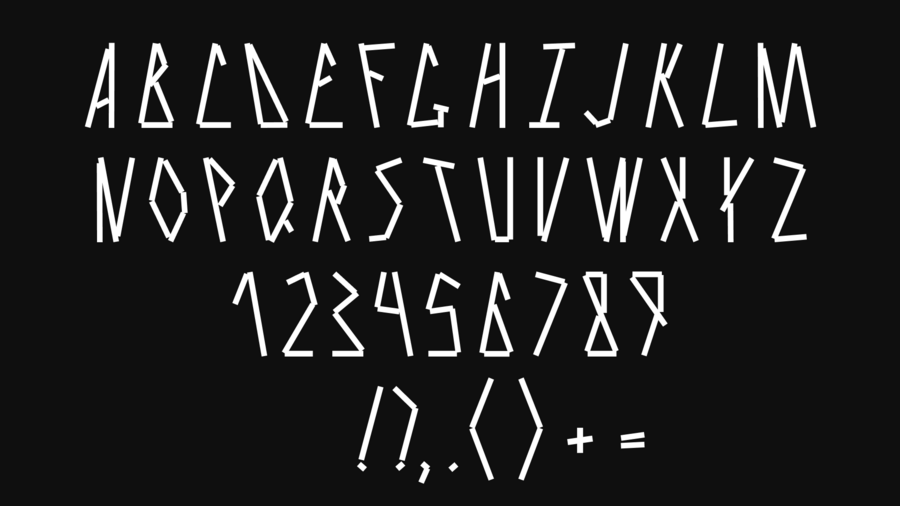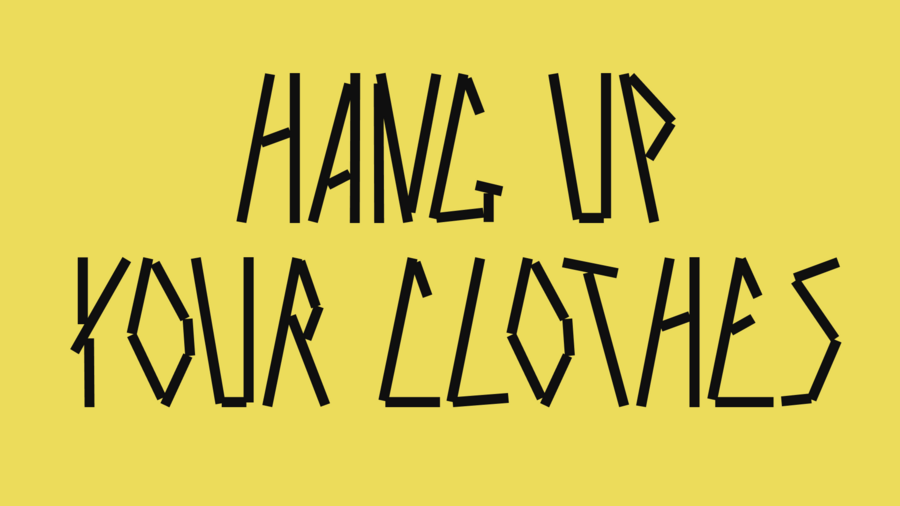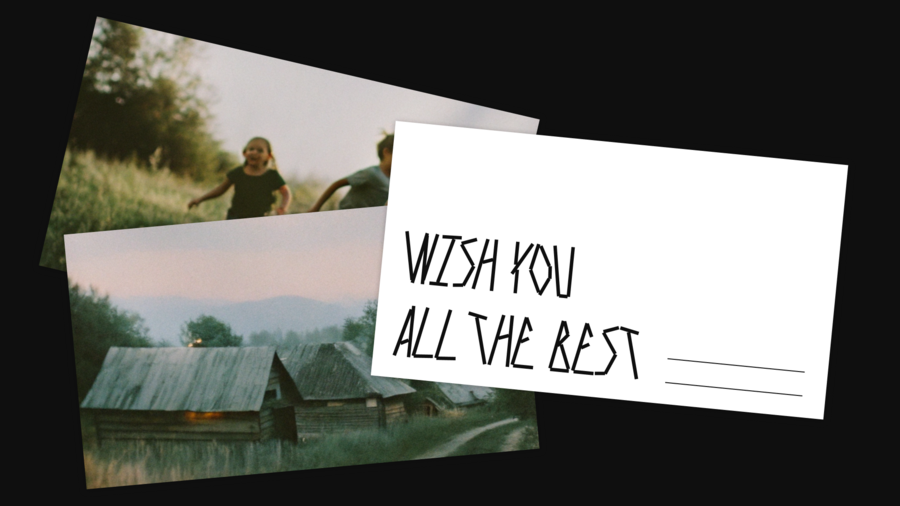
prishchepka font — акцидентный шрифт, вдохновлённый конструкцией, угловатостью и характерным изломом деревянной прищепки. в нём ощущается механическая простота и неловкость ручного предмета
prishchepka font